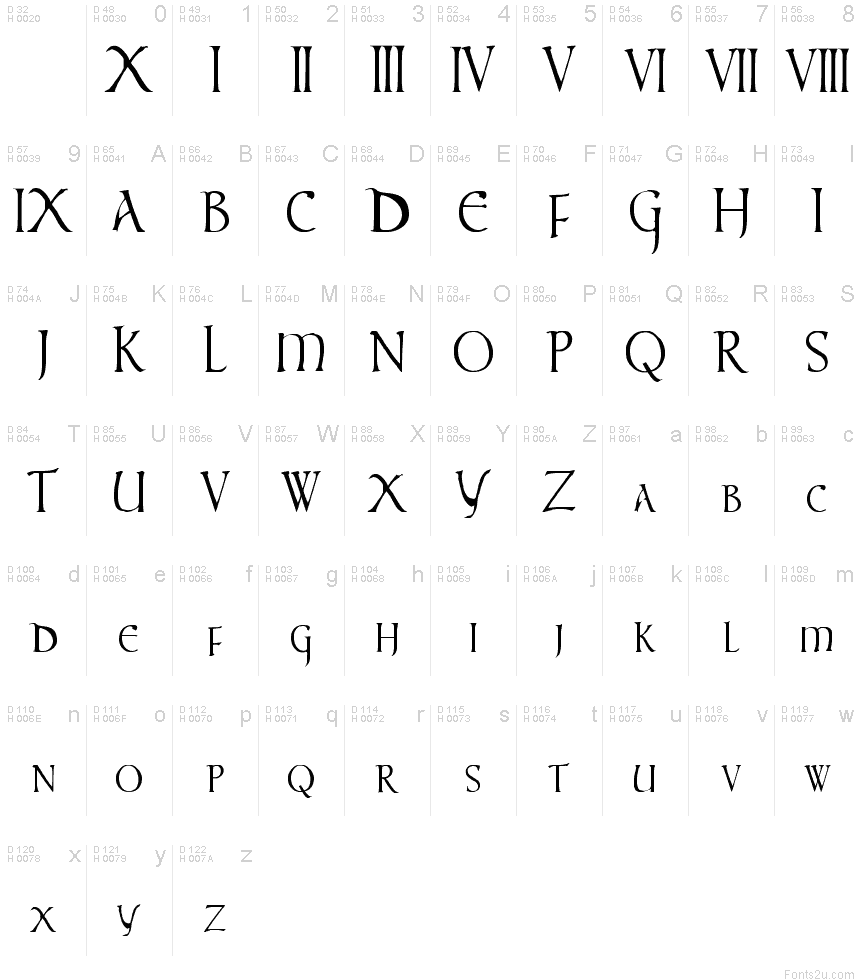
Times New Vespasian di Paulo W è un font display gratuito ispirato all'antichità romana che trasforma un familiare carattere da giornale in qualcosa di più cerimoniale. Le lettere abbinano un contrasto netto a grazie larghe e solenni e a un ritmo del vecchio mondo leggermente scolpito, rendendo l'impressione generale più classica che letteraria.
Questo conferisce al font un impiego naturale in copertine di libri, poster museali, testate editoriali, titoli e monogrammi, dove è richiesto un tono storico sobrio. Funziona al meglio nelle composizioni brevi, poiché le maiuscole hanno abbastanza slancio e autorità per reggere un nome o una riga di apertura senza bisogno di altro.